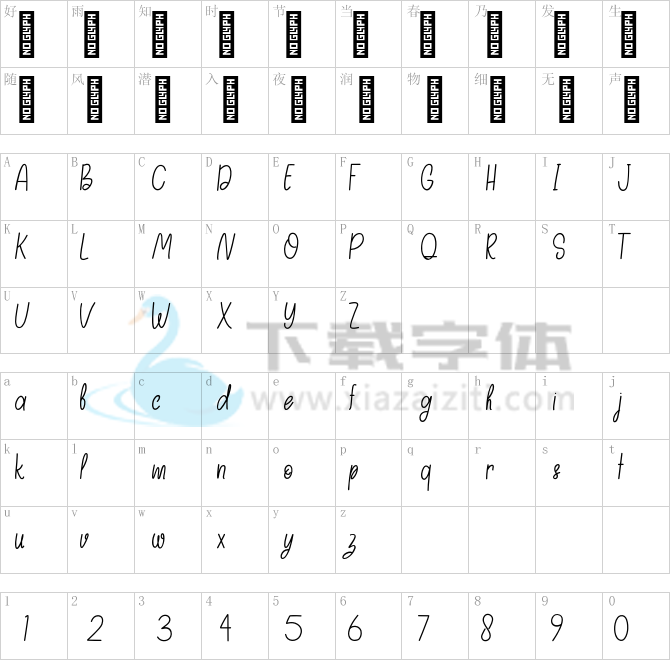
Autumn Days - Personal Use.otf字体下载,这款字体结构工整、笔画清晰,兼顾美观与易读性,适用于标题、正文、海报、包装、LOGO 等多种场景。字形优雅稳定,风格百搭耐看,适配日常排版与创意设计,让文字呈现更舒适、更具质感。Autumn Days - Personal Use.otf字体下载一笔一画,皆是细节,以均衡的比例、流畅的线条打造舒适视觉体验,字形端正大气,风格简约现代。无论是商业设计、品牌宣传还是日常排版,都能轻松驾驭,让文字更有格调与力量。Autumn Days - Personal Use.otf字体下载字体下载。